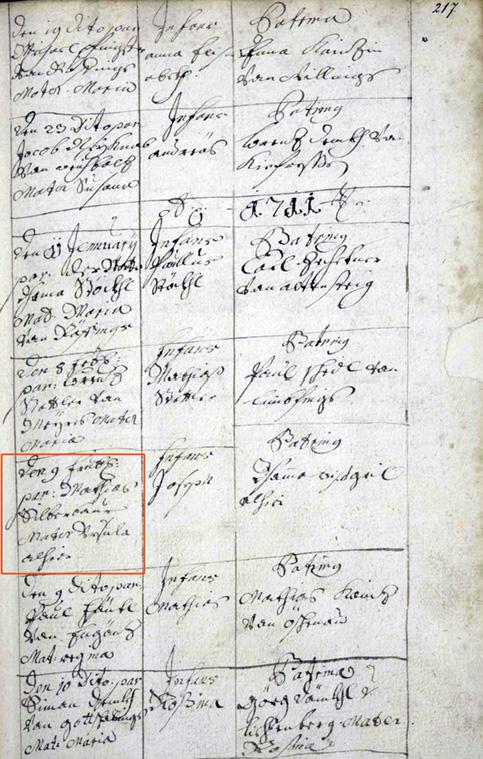
Hilfe beim Entziffern (Kurrentschrift)
ich beschäftige mich seit zwei Tagen mit einem Dokument und konnte schon einiges entziffern, nur diese zwei Zeilen kann ich partout nicht "übersetzen". Kann mir jemand helfen, der mehr Erfahrung mit Kurrentschrift hat?
Die erste Zeile ist ein Familienname, die zweite Zeile die Ortschaft, aus der die Person stammt.
Erst einmal ist es immer schlecht, wenn man nur 2 Worte, die noch dazu als Namen keine alltäglichen Worte sind, zum Erkennen bekommt. Je mehr sinnvollen Text man hat, um so eher kommt man hinter die Schreibweise bestimmter Buchstaben des Schreibers. Auch wenn man mehr Einträge des wahrscheinlichen Kirchenbuchs hat, kann man da auf die Region schließen, und hat vielleicht bekanntere Ortsnahmen in der Umgebung, von denen aus man auch den gesuchten Ort finden kann.
Catfont hat recht - man muß in der Regel so viel Text wie möglich sehen, um da etwas auszumachen. Auch ist dies u. U. Nicht das richtige Forum hierfür.
Trotzdem wage ich es mal: Riebekin v. Edelprinz.
Ich vermute ein "K" am Anfang, also Kiebekin v[on] Edelprinz.
Hier gibt's ein Sammlung von Dokumenten (habe nicht genau geschaut, worum es sich eigentlich handelt). Da tauchen ganz viele Kiebekins (oder in anderer Schreibweise: Kühbekin, Küwekin etc.) auf, alle mit dem Zusatz "von Edelprinz".
Jetzt sehe ich das auch so, jedoch lese ich eher Kiebekin. Und mir diesem Text fand ich in Google eine Textstelle, die allersungs keine wirklich hilfreichen Informationen bietet:
"Kiebek von Edlprinz Philipp Tenk von Nondorf Hebamme: Kiebekin v. Edelprinz Fol. 38"
Immerhin ist Edelprinz ein Ortsteil von Waidhofen an der Thaya-Land in Niederösterreich, ein anderer Ortsteil ist Nondorf, und hier befanden sich unter den Geburtseinträgen eben auch ein Eintrag:
Fol. 37) 7. 8.1790 lEschenau No.3
* Michael
Joh Georg Biedermann
Theres. Kühbeckinn v. Edelprinz
Philipp Denk v. Nondorf
Hier ist auch noch eine Fundstelle für Kiebekin v. Edelprinz, Hebamme:
* Mathäus Johann Georg Bittermann Bauer
Theresia geb. Kiebek von Edlprinz
Philipp Tenk von Nondorf
Hebamme: Kiebekin v. Edelprinz
Fol. 38) 18. 3.1799 Eschenau No.3
Darf ich ein zweites und letztes Mal um Hilfe bitten? Es geht um die 3. Zeile der in rot markierten Stelle im angehängten Dokument.
Ich glaube zu erkennen:
den 9. Februar
Par: Mathias
????? (den Nachnamen kann ich nicht entziffern)
Mater Ursula
Allhier
Spontan hätte ich "Silbermann" gesagt. "Silb" ist gut lesbar; "er" ist auch wahrscheinlich, wenn man's mit dem "alhier" drunter vergleicht. Die folgenden Buchstaben sind aber schwierig. Zunächst ein Kringel, der wie ein Schluss-s aussieht. Gibt es den Namen "Silbersman[n]"? Und dann gibt's noch den umgedreht-s-förmigen Kringel, der wie der Überstrich für ein "u" aussieht; aber wo soll das "u" hin?
Vielleicht hatte der Schreiber auch einen schlechten Tag. Wenn man sich den Eintrag darüber anschaut, ist z.B. "Febs" als Abkürzung gut lesbar. In der markierten Spalte hat sich aber noch ein Buchstabe eingeschlichen, wo gar keiner sein sollte.
Man ist wohl auf den Kontext verwiesen, um den Namen zu verifizieren. Vielleicht weitere Einträge im Umfeld, wo der Name des taufenden Geistlichen besser lesbar ist?
"Silbermann" scheint sehr plausibel.
Ich habe gehofft, dass es sich Biedermann oder Bittermann ergibt, aber man tendiert eben dazu, das zu lesen, was man finden möchte, was sehr gefährlich ist...🙂